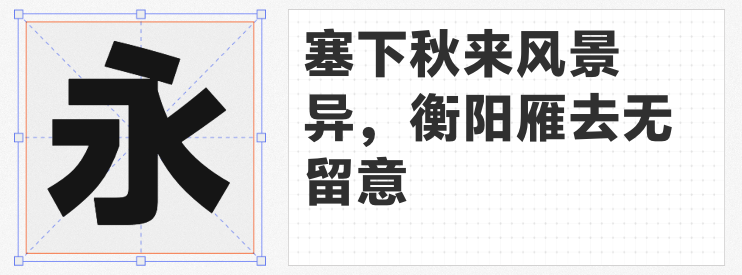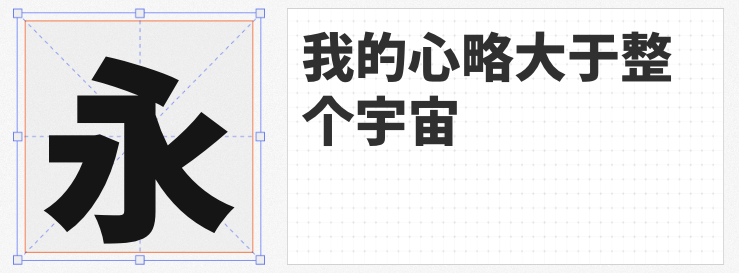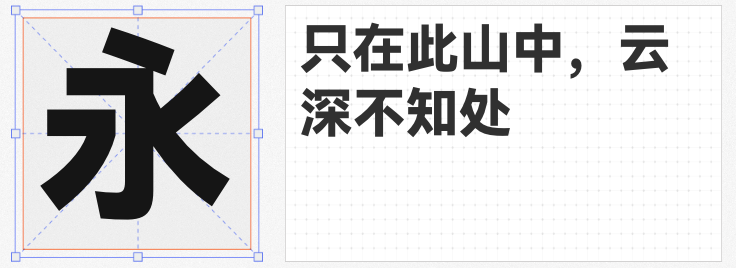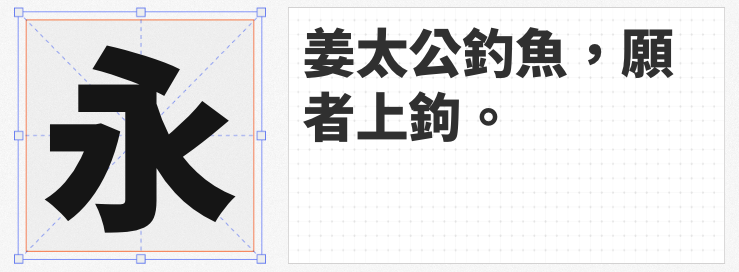
在视觉设计领域,超粗黑体以其强烈的视觉冲击力和现代感,成为标题、海报、品牌标识等场景的优选。本文精选四款免费商用超粗黑体字体,兼顾设计美学与实用功能,为设计师提供高效解决方案。
华为定制的HarmonyOS Sans SC Black以“功能性优先”为设计理念,在短笔画中保持横平竖直的简洁线条,长笔画则融入书法笔势美学,形成刚柔并济的视觉张力。其字形结构方正,重心居中,中宫适中,确保多语言环境下的统一性,支持简体中文、繁体中文、拉丁、西里尔等105种语言。作为鸿蒙系统原生字体,它不仅适配数字屏幕,更通过优化灰度分布提升小字号阅读体验,适合科技品牌、数字界面等场景。
基于思源黑体改造的梦源黑体TW W27,通过二次多项式插值算法生成27级字重(W1-W27),覆盖从纤细到超粗的完整梯度。其设计合并了重叠曲线轮廓,减少文件体积的同时提升渲染效率,尤其适合需要多字重过渡的动态设计。字体支持完整CJK字符集(含简繁日韩),并修复了思源系列行高过大的问题,在Word、PowerPoint等软件中表现稳定,是电商海报、品牌视觉系统的理想选择。
vivo Sans Heavy以91%的大字面率提升文字识别度,通过均匀布白、部件比例优化和笔画避让设计,实现视觉协调与易读性的平衡。其勾画采用趋平式设计,贴合屏幕像素分布,减少锯齿感;西文字体延续中文的无衬线风格,x高较高,字腔开阔,确保跨语言场景下的统一性。作为免费商用字体,它适用于移动端UI、长文本阅读等需要高效传达信息的场景。
基于思源系列衍生的尚古等宽H,融合黑体、明体、圆体风格,并支持简转繁功能。其等宽设计使字符宽度统一,适合代码编辑、数据表格等需要对齐的场景,同时保留超粗字重的视觉冲击力。字体采用SIL Open Font License 1.1协议开源,允许自由修改与再分发,为文化创意、教育出版等领域提供灵活的用字方案。